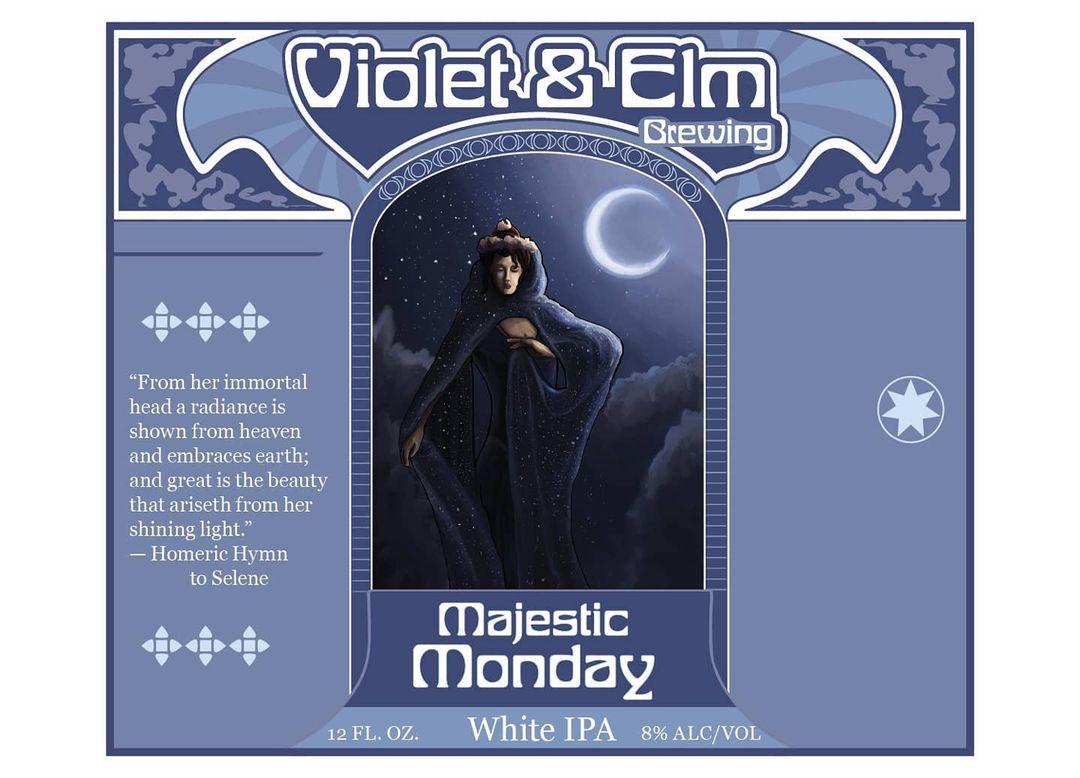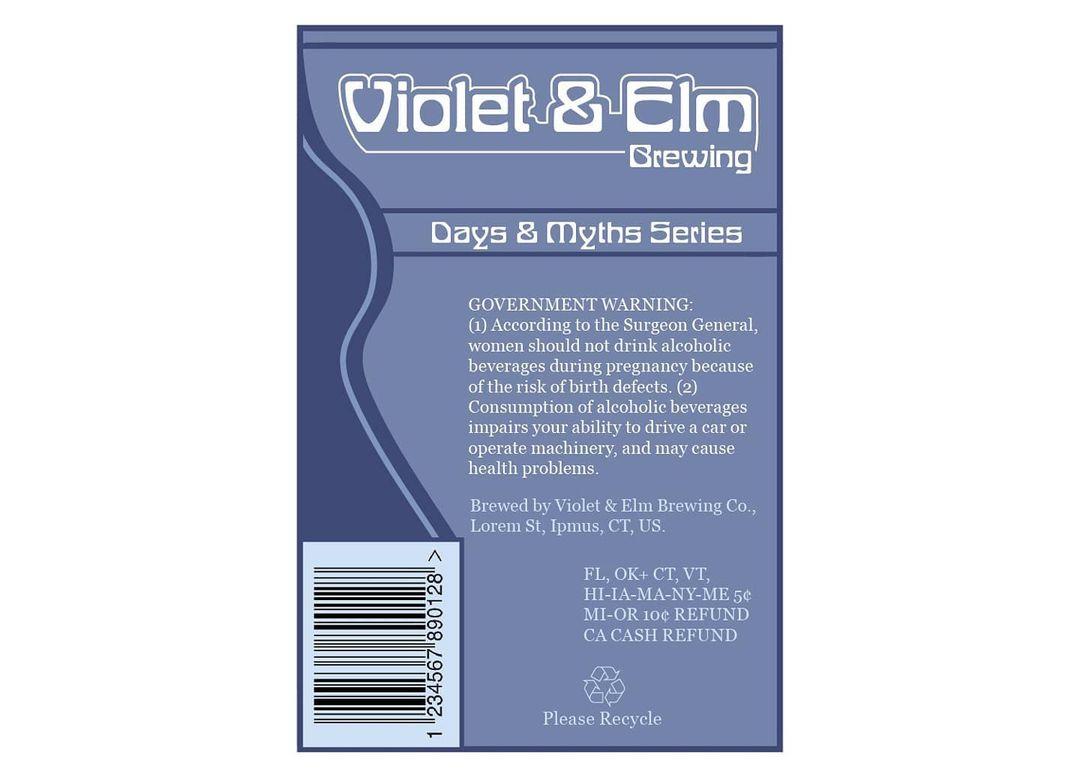
Als Historiker widerspreche ich da mal. Die Kommentare kann ich als Quelle, als oral history, begreifen. Eine damnatio memoriae von Termini führt nicht zu einem anderen Verhalten.
Ich will mich eigentlich zu dieser Diskussion nicht weiter äußern, aber gerade in diesem Zusammenhang hat mir eine bereits etwas ältere Rede von Rowan Atkinson (2018) gut gefallen.
Zusammenhang
Wobei sich dieser Zusammenhang hier für mich nicht ergibt. Es ging um eines dieser, wie ich finde, lächerlichen Gesetze, mit denen der Überwachungsstaat Großbritannien versucht, seine Bürger zu disziplinieren. Es geht hier um Begrifflichkeiten, unter deren Geschrei Menschen getötet wurden (beispielsweise alle Formen, die sich von niger ableiten, oder wie jenes Wort, das mit Z anfängt, was man Menschen in Auschwitz auf den Arm tätowierte).
Der Zusammenhang ist daß man über das rein Sprachliche hinaus sehen sollte. Eine Interpretation der Inhalte ist eigentlich viel wichtiger. Ich meinte folgende Aussage von Dir: »Niemandem ist geholfen, wenn wir People of Color zwar so benennen, sie aber weiterhin so behandeln [wie vorher].« Wie hieß doch gleich der Sprachwissenschaftler der lange an der Uni Bremen gearbeitet hat? Anatol Stefanowitsch. Der hat vor einigen Jahren mal sinngemäß sehr richtig gesagt: die genaue Wortwahl ist eigentlich völlig unerheblich. Es gibt eben nicht immer völlig unbelastete Begriffe, und das muß es auch gar nicht. Aber es ist wichtig daß die Wortwahl eindeutig zeigt daß es ein Problem gibt und daß ich mir des Problems bewußt bin und versuche die Situation zu verbessern. Solange dieser Sachverhalt erfüllt ist, ist die genaue Wortwahl eigentlich nicht so wichtig und man sollte sich nicht in unendlichen Diskussion allein zur Wortwahl verstricken.
Habe heute zum ersten Mal eine meiner Jugendstilschriften in freier Wildbahn (naja, auf Instagram, und leider nur Konzept) gesehen. Etiketten für Flaschenbier mit WF Wallenstein. Den Fließtext hätte ich mit WF Schelter Antiqua gemacht, aber da gibt es wohl Auflagen. Zumindest die Warnung sieht auf allen Bieren gleich aus.
ALDI-PaleAle?
Das ist ja wirklich von ALDI … :-|
Von CREW REPUPLIC gibt es ein IPA mit 3,4 % Alk. Da kann man ein oder zwei Bier trinken ohne gleich tüdellig zu sein 🍻
Wurde grad auf San Seriffe aufmerksam gemacht 🙂
Teaser:
San Serriffe ist ein fiktiver Inselstaat, der von der britischen Zeitung Guardian als Aprilscherz im Jahr 1977 erfunden wurde. Der Inselstaat habe die Form eines Semikolons, die Hauptstadt hieße Bodoni und der Name des politischen Führers sei Pica, ein unbeliebter General.
Wird seit vielen Jahren hier im Forum am April, April gern genommen:
Das wusste ich nicht, aber ein wenig Auffrischen schadet ja nicht.
Wie sind denn dort die aktuellen coronabedingten Einreisebestimmungen?
Mit welchen Font muss bspw. die Testbescheinigung gedruckt sein?
Ich hab eine Zeitlang gerätselt, was "Futurels" sind …
....    gerätselt...       Das ist wie mit dem  Kuhliefumdenteich.  Wenn man auf Wortabstände verzichtet.
Und dann noch die ollen Griechen! Ohne Zwischenräume und abwechselnd links- und rechtsläufig.  Der Ausdruck dafür ist eines meiner Lieblingsworte: bustrophedonisch